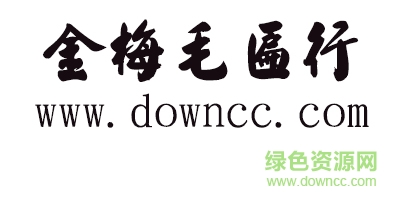
金梅毛匾行
金梅毛匾行字體風(fēng)格獨(dú)特,字體外形比較規(guī)范。使用這款字體設(shè)計(jì)的文字效果很不錯(cuò)!在機(jī)械印刷設(shè)計(jì)行業(yè)、平面設(shè)計(jì)行業(yè)使用到的比較多!歡迎選擇安裝。
金梅毛匾行字體是金梅字體庫里的一款字體,該字體字形端正,一筆一畫,規(guī)規(guī)矩矩。適合用于廣告設(shè)計(jì)、雜志報(bào)刊等領(lǐng)域。有喜歡的朋友趕快來綠色資源網(wǎng)下載使用吧!
金梅毛匾行字體